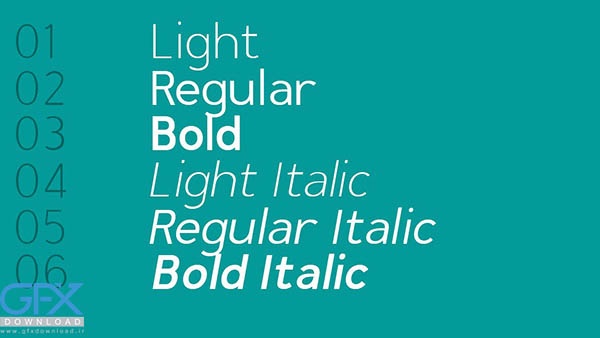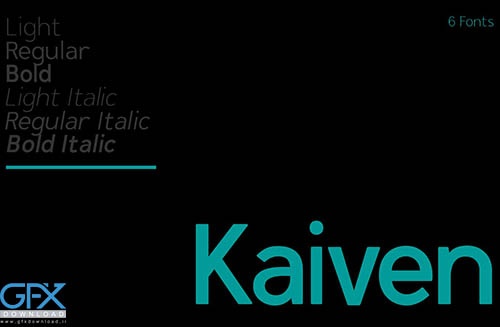
فونت رایگان Kaiven
دانلود رایگان فونت Kaiven
دانلود رایگان فونت انگلیسی Kaiven
طراحی بسیار ساده، تمیز و مینیمال، این فونت برای استفاده روزمره، کارهای شخصی یا تجاری مناسب است. خواندن این فونت بسیار آسان و بسیار متنوع است. این فونت رایگان Kaiven در شش سبک ارائه می شود: سبک، منظم ، پررنگ، کج روشن، کج معمولی ،کج و با حروف درشت